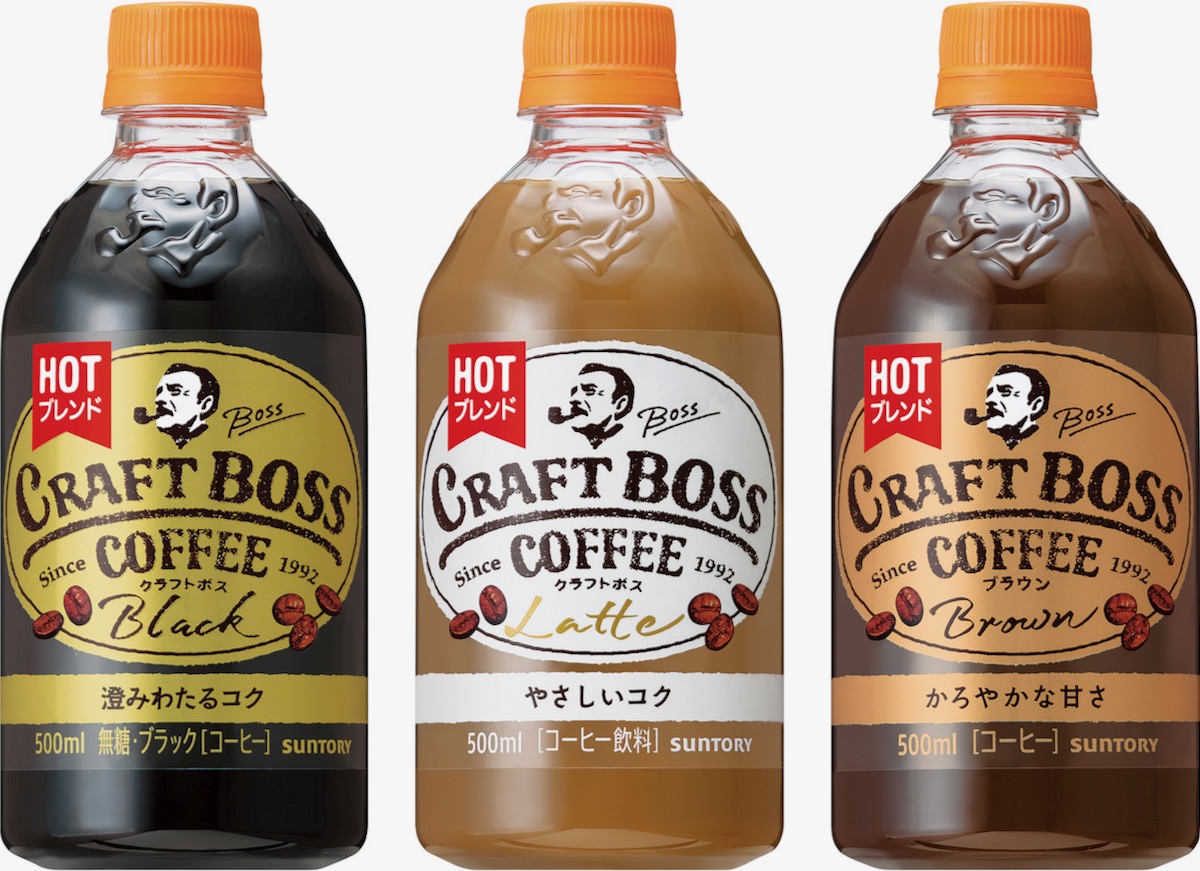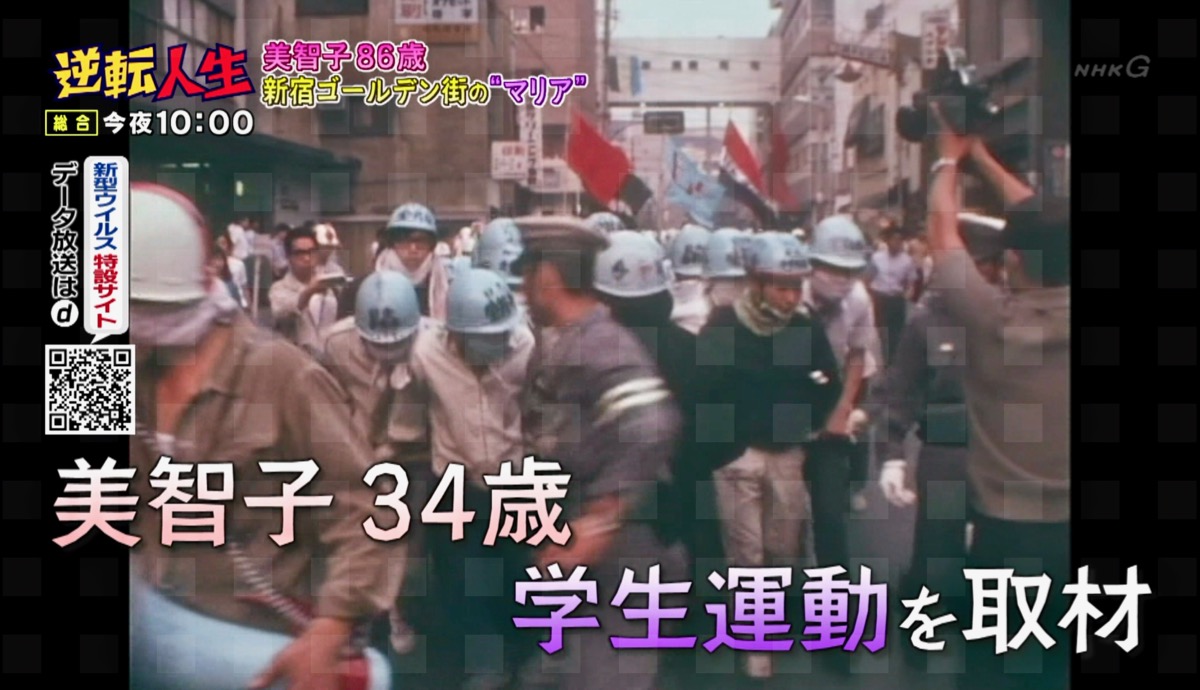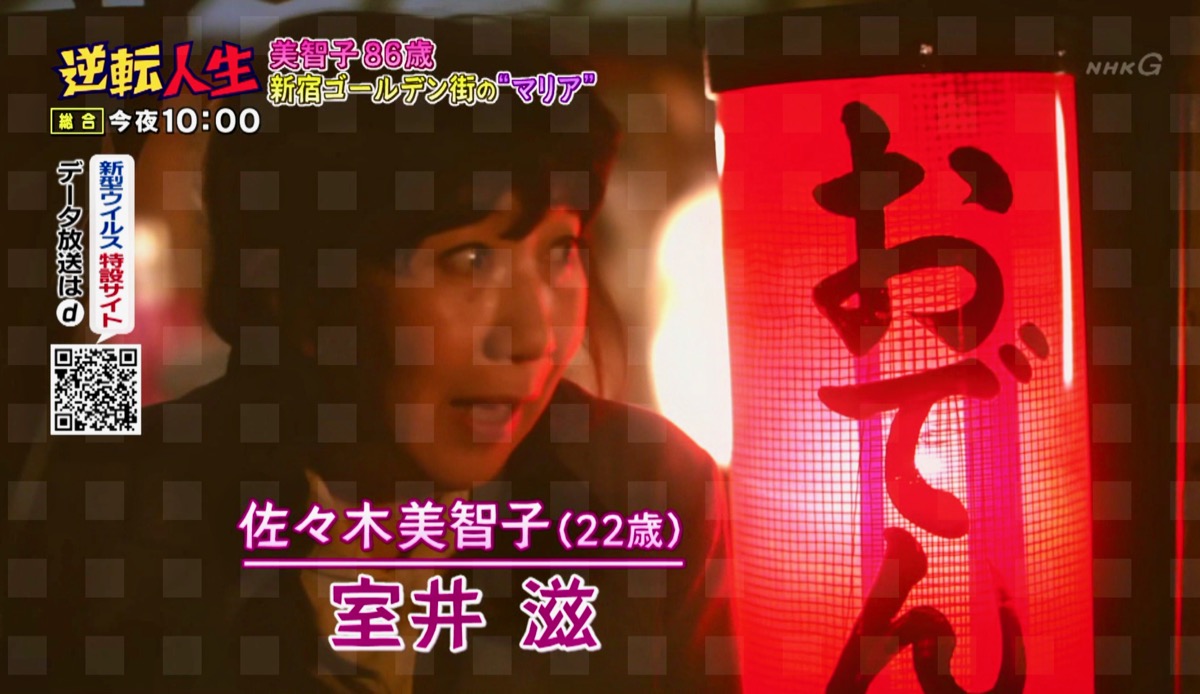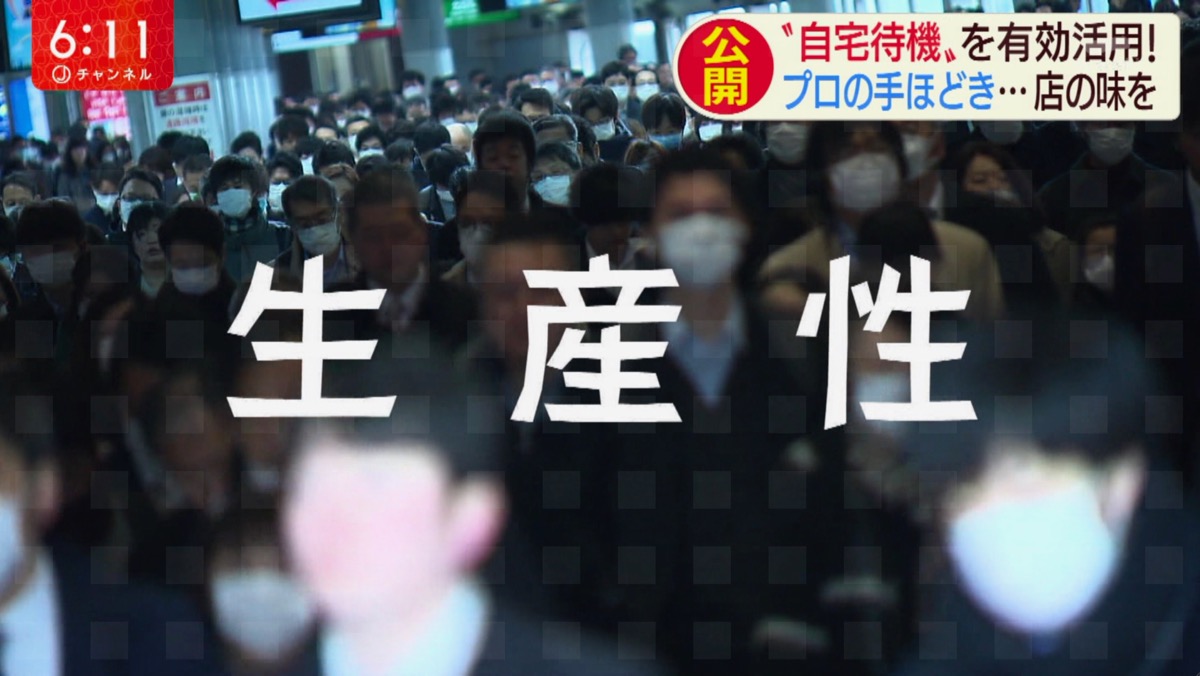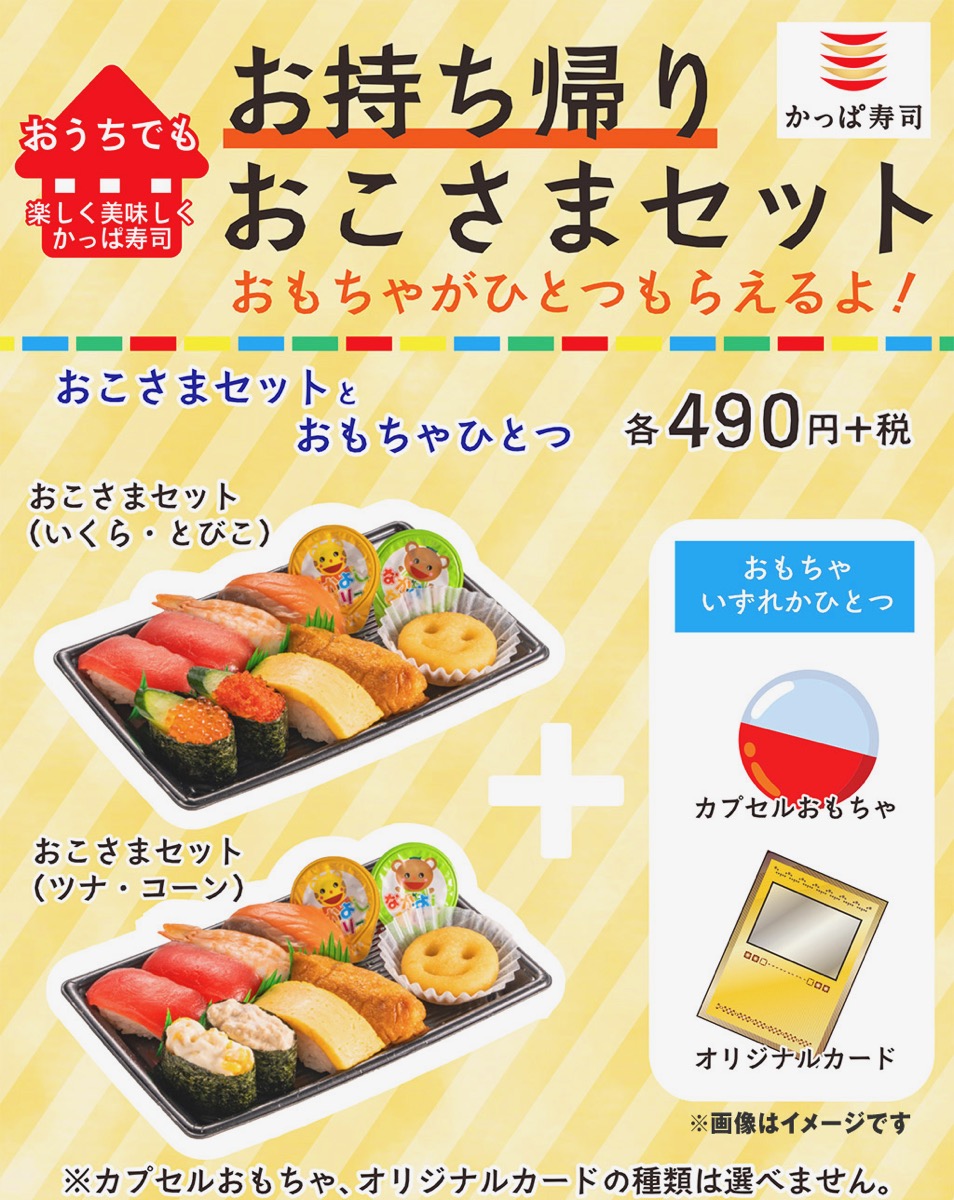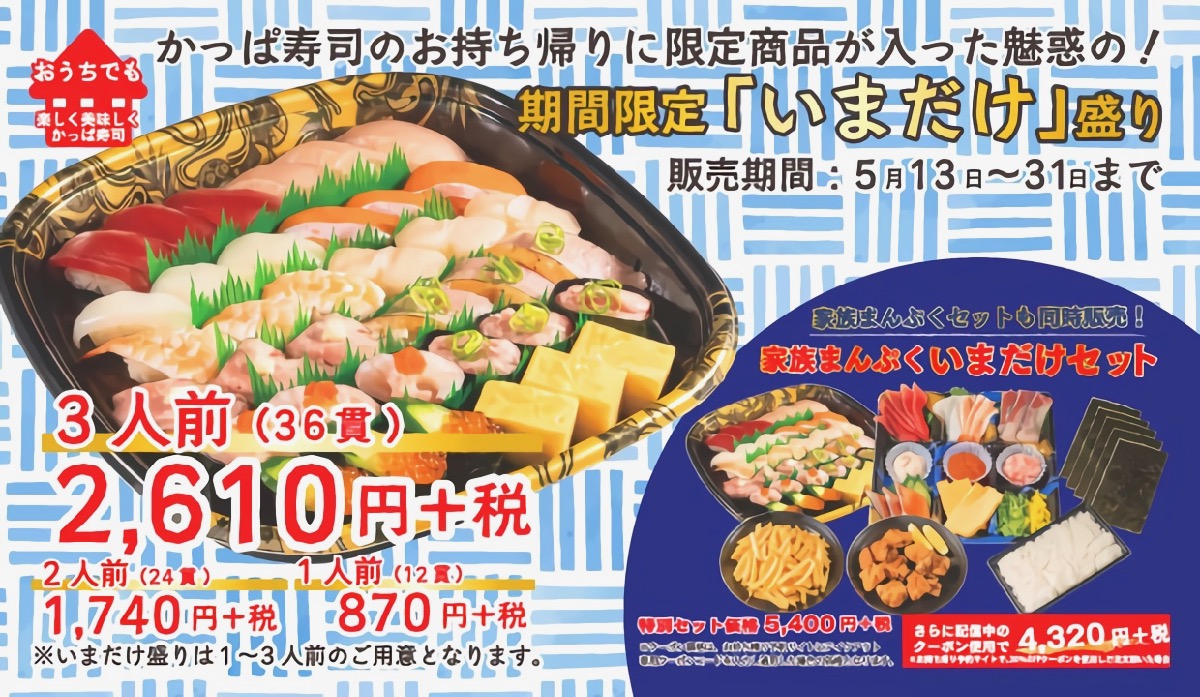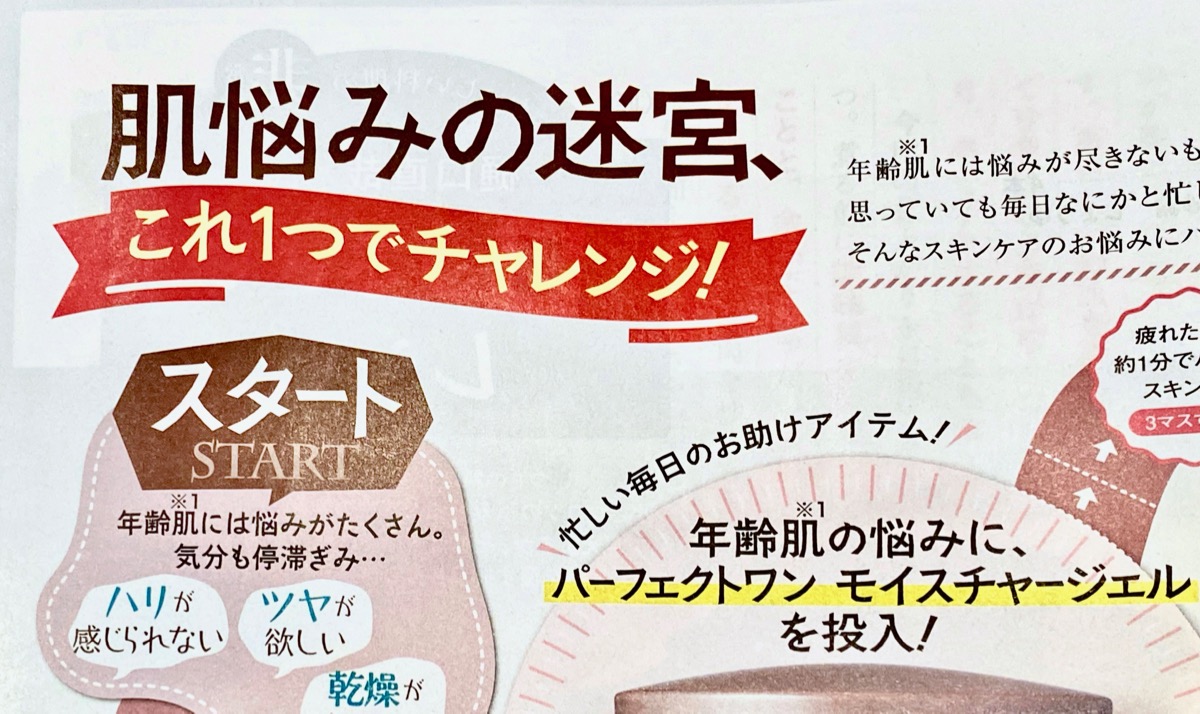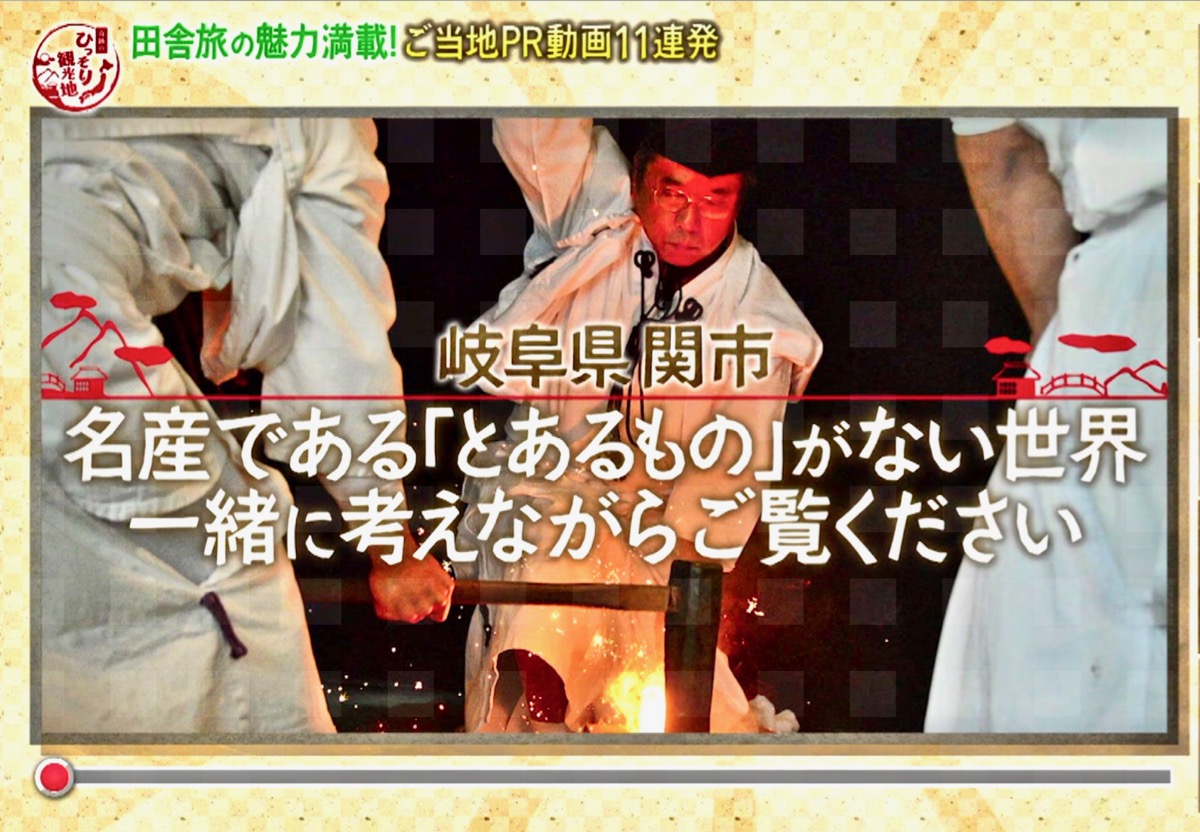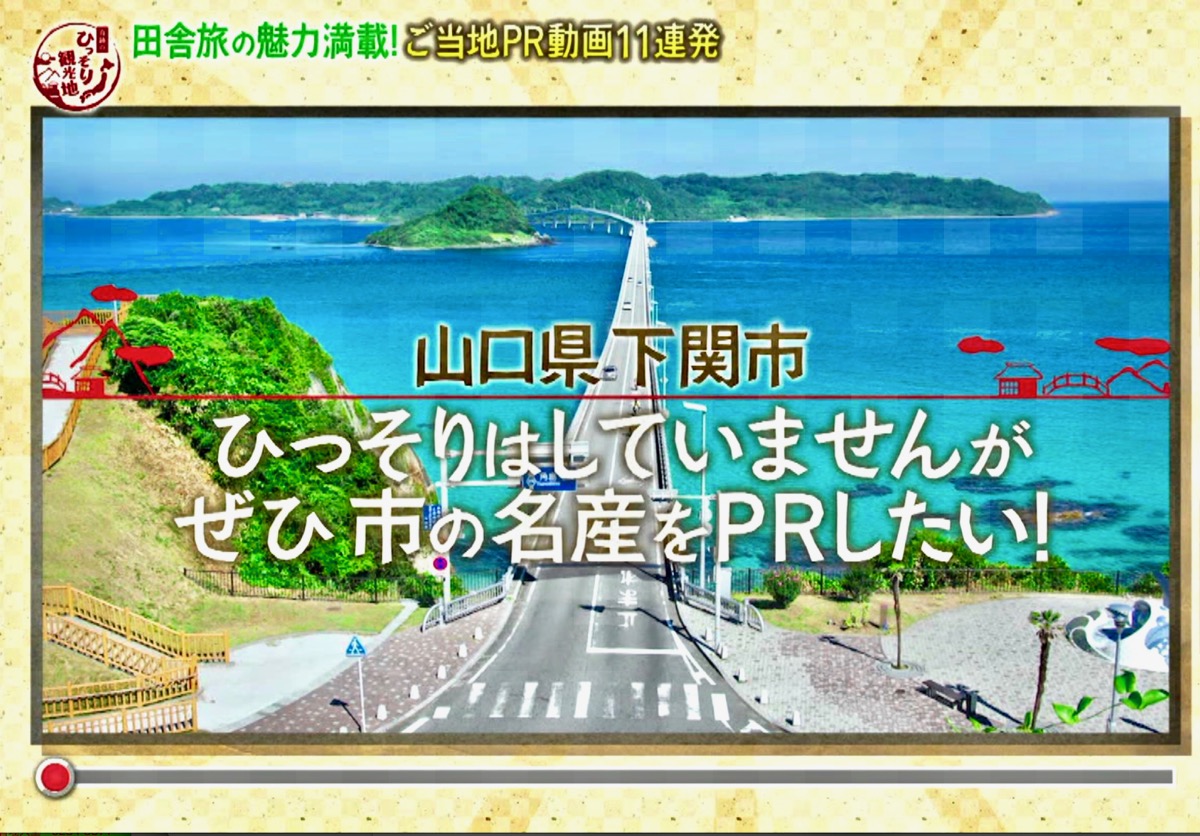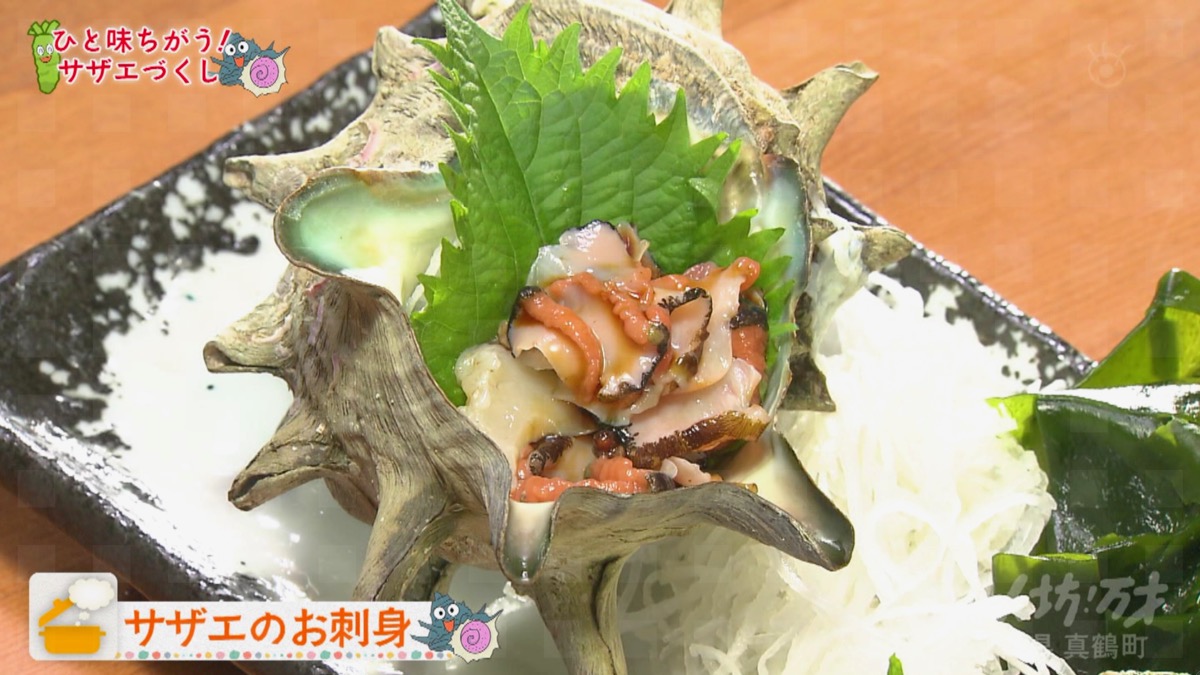
「英検で海外留学」の案内ページの画像上で「あられ」フォントがちょこちょこ使われているようです。
白抜きの、「英検で〜切り開く!」の部分ですね。
もう1枚。
赤背景に白抜きのバナーと、その下の「ポイント1〜4」の下の文字も「あられ」ですね。
いくつか前の他の方の投稿で「洋風でも和風でも合う」と書かれていましたが、まさにこれは洋物(笑)かな?
ひらがな部分は他の書体です。
書名:焚き火料理の本
著者:小雀陣二
発行:山と溪谷社
もう1冊ありました。
書名:焚き火の本
著者:猪野正哉
発行:山と溪谷社
フォントは高いからプロや企業が買うものと思っていましが、個人でも買える値段だったので購入しました。メールのコピーが残っていましたが、19年前でした。(当たり前ですが、メールにはさとうさんのお名前がありました。)
15年前には等幅も買っています。
それ以来、プレゼンのタイトルなど、ここぞというところで使わせていただいています。
個性的なのに主張が強すぎることがなく、洋風でも和風でも合う。半角英数字も含めて、ほれぼれするかっこ良さです。
NHKでよく見るなあと思っていたのですが、あちこちで使われているのですね。
19年前のご購入ですか、発売してすぐの頃ですね。
そんな前から使っていただいて、こちらこそ感謝しております。
まったく関係ないですが、最近ネットで見つけた使用例を掲載します(笑)。
読売テレビ(関西圏)で放送されている「そこまで言って委員会NP」という討論番組で使われていた「あられ」フォントです。
参考にもう1枚。
東京では見られない番組のようですね、残念!
カルディで販売されているようです…。
ファミマ限定商品です。
これがパッケージかな。
別商品のため新スレッドで失礼します。
ミツカンのふりかけ「おむすび山焼きたらこ」の「焼きたらこ」があられです。
こちらは裏面。直撮り失礼します…
料理研究家による人気のレシピサイト「白ごはん.com」のロゴ(サイト左上)があられみたいです。
全体的に太めなのと「は」に調節が入っています。
こんなに小さなロゴなのに…、よく気づいてくれました…。
使用例でなく恐れ入りますが…
フォントワークスの学生用ライセンスで一番好きなフォントがあられでした。読みやすさと手作り感の合わさった雰囲気が好きで、また使いやすく愛用しています。
私にとっては、ずいぶん前に作った懐かしい書体です。
しかし、いまでも使ってくれる人がいて、使用例を目にすると嬉しいものです…。
漫画雑誌内の見開きページを使った次号広告。